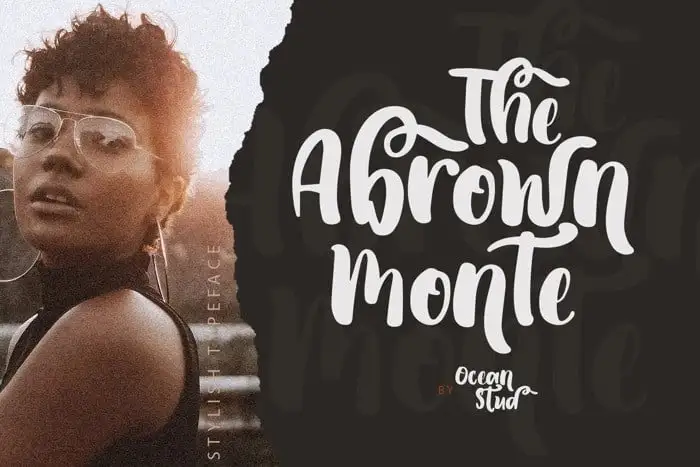
The Abrown Monte Script Font – Download Grátis
A fonte The Abrown Monte Script Font é uma opção elegante e criativa para projetos que buscam aperfeiçoar sua identidade visual. Ela traz um estilo autêntico e delicado, feito à mão por The Ocean Studio. Com suporte para letras maiúsculas, minúsculas, símbolos e até mesmo múltiplas línguas, esta fonte é perfeita para qualquer projeto profissional que deseje destacar seu trabalho de uma maneira única. É especialmente adequada para logotipos, branding, criação de casamentos e citações. Com um design atraente e sofisticado, The Abrown Monte Script Font é certamente o elemento ideal para tornar suas mensagens ainda mais impactantes e memoráveis.